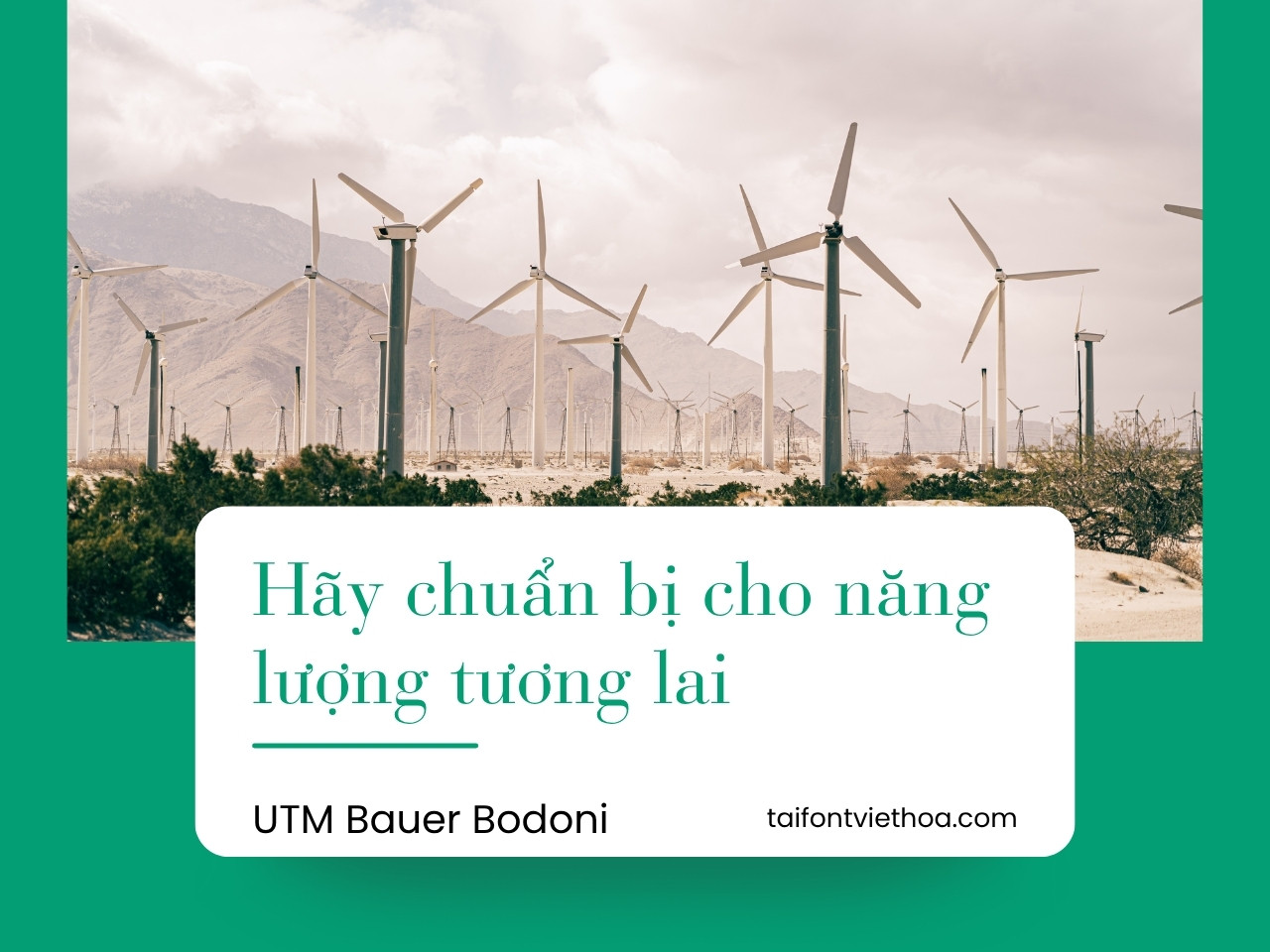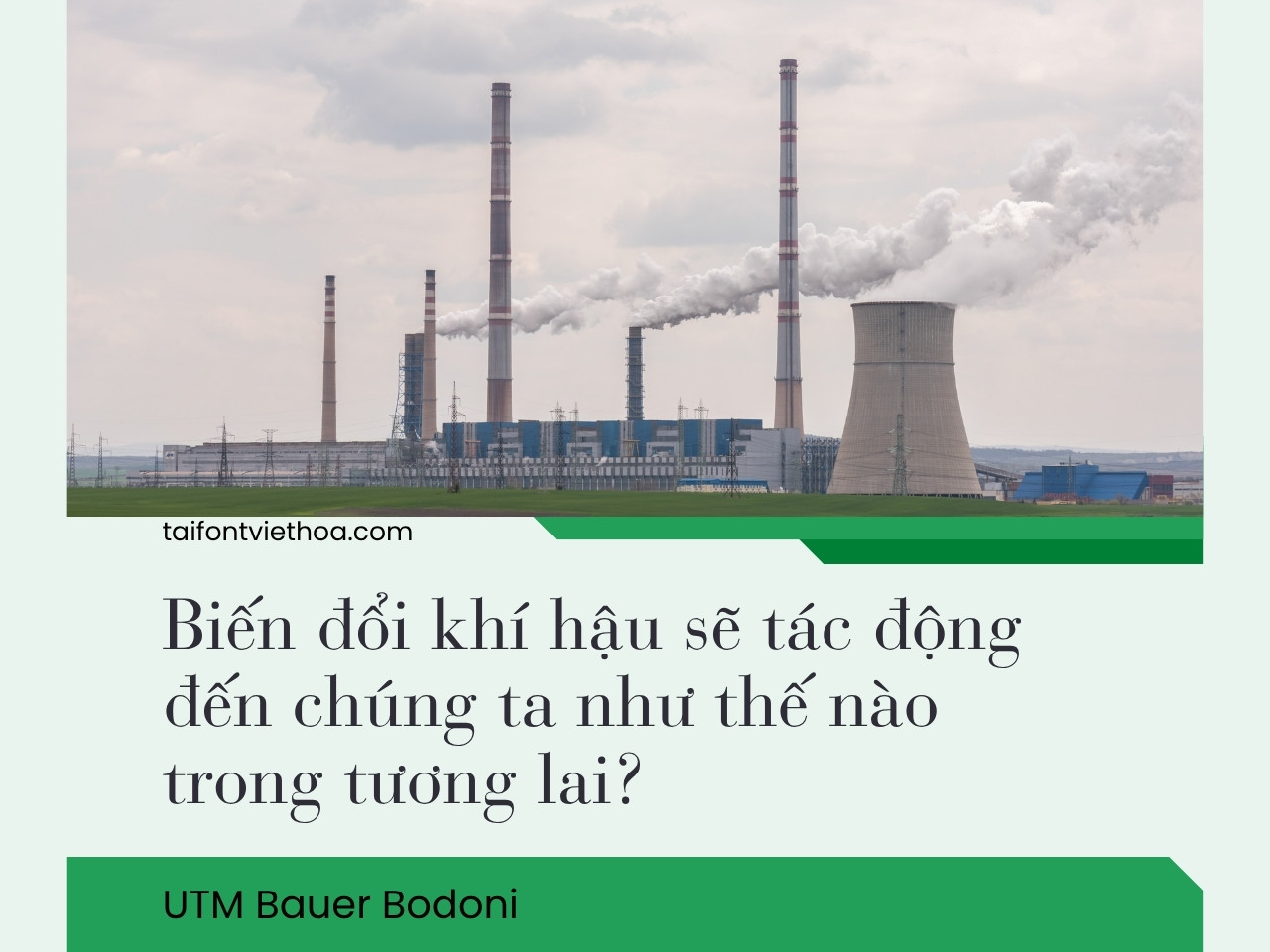
Font việt hóa UTM Bauer Bodoni
Giới thiệu về font UTM Bauer Bodoni
UTM Bauer Bodoni là phiên bản Việt hóa của font Bauer Bodoni – một trong những kiểu chữ serif nổi tiếng nhất, được thiết kế bởi nhà thiết kế Giambattista Bodoni vào cuối thế kỷ 18. Font gốc nổi bật với các nét chữ có chân (serif) sắc nét, độ tương phản cao và cấu trúc cân đối, mang lại vẻ đẹp thanh lịch và sang trọng. Phiên bản Việt hóa đã được hoàn thiện để hỗ trợ đầy đủ tiếng Việt và hơn 200 ngôn ngữ khác, giúp mở rộng khả năng sử dụng trong các dự án thiết kế cao cấp.
Font UTM Bauer Bodoni được taifontviethoa.com sưu tầm và chọn lọc kỹ lưỡng nhằm phục vụ cộng đồng thiết kế Việt Nam. Phiên bản Việt hóa giữ nguyên tinh thần cổ điển và sang trọng của bản gốc, đồng thời tối ưu khả năng hiển thị tiếng Việt, phù hợp với các dự án branding, xuất bản và quảng cáo cao cấp.
Đặc điểm thiết kế và ứng dụng của UTM Bauer Bodoni
UTM Bauer Bodoni sở hữu cấu trúc serif với các nét chân chữ sắc nét, độ tương phản cao và thiết kế cân đối, tạo nên sự thanh lịch và dễ đọc. Font phù hợp cho cả nội dung văn bản dài và tiêu đề nổi bật. Ngoài ra, font còn được trang bị nhiều ligature và glyph thay thế giúp tăng tính linh hoạt trong thiết kế.
Font thích hợp sử dụng trong các ứng dụng như thiết kế sách, tạp chí, thiệp cưới, danh thiếp, bao bì sản phẩm cao cấp và các ấn phẩm thương hiệu sang trọng. Các ngành nghề phù hợp gồm: xuất bản, thời trang, tổ chức sự kiện, nghệ thuật, giáo dục và thiết kế nội thất.